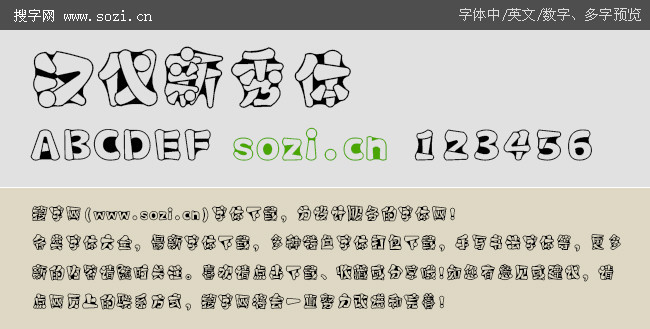
漢儀新秀體
搜字網(wǎng)提供一款漢儀新秀體中文字體下載,新秀體結(jié)合了涂鴉字體和POP字體這兩款美術(shù)字,并將其注入新鮮血液,使字體充滿年輕活力,線狀的曲線搭配面狀的陰影,讓字體躍然紙上,層次感突出而鮮明。適合標(biāo)題設(shè)計(jì)、畫冊(cè)設(shè)計(jì)、海報(bào)設(shè)計(jì)等場(chǎng)合使用。(本字體為個(gè)人非商用版,如需要商用請(qǐng)聯(lián)系漢儀公司購(gòu)買版權(quán))